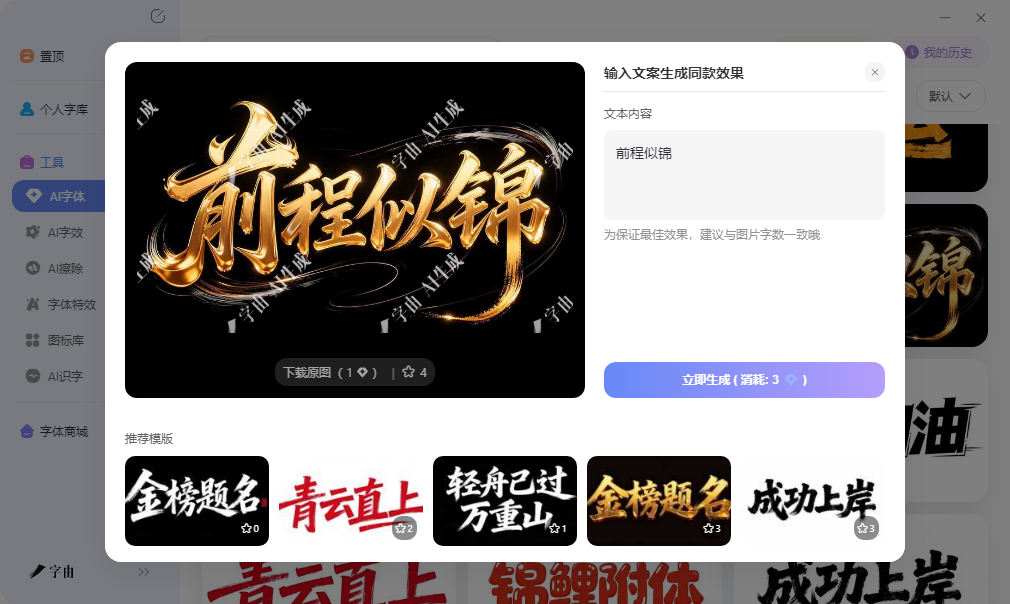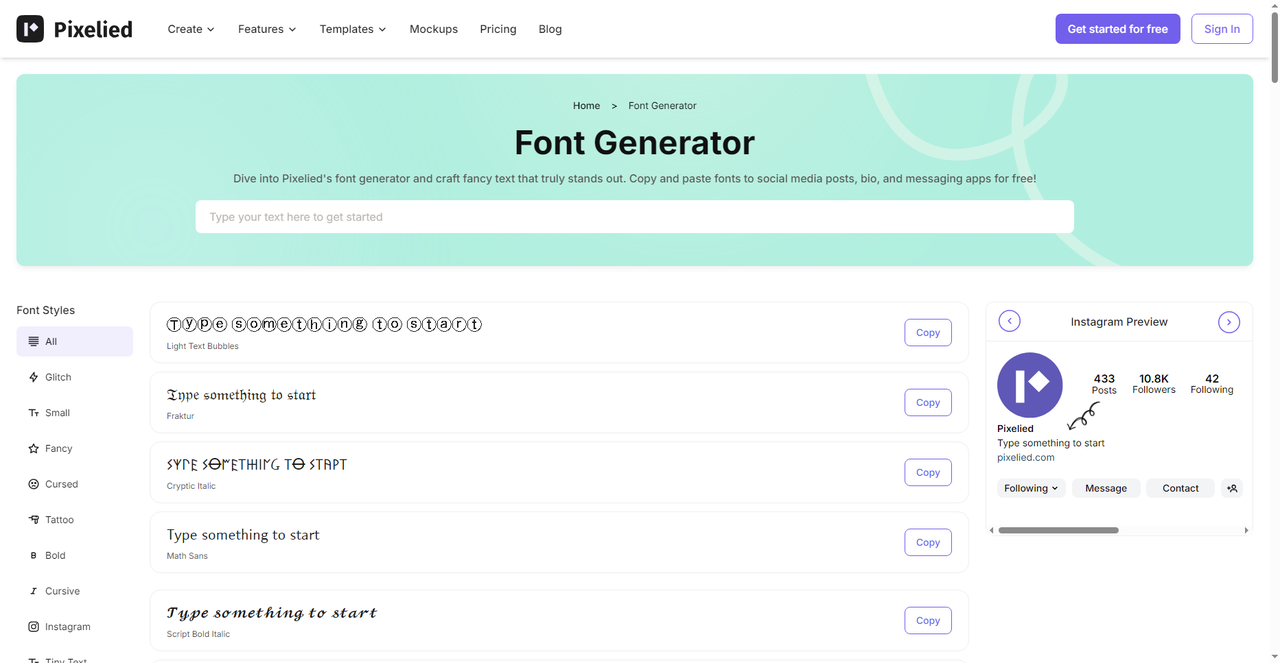
社交媒体上那些带特殊效果的文字,看起来像是用了什么高级设计软件,其实有不少在线工具可以直接生成。输入文字、选一个风格、复制粘贴就能用,不需要安装任何软件。这篇文章整理了五个艺术字体在线生成器免费平台,从中文AI艺术字到英文装饰字体都有,适合做海报标题、社交账号简介、游戏昵称等场景。
字由的AI字体功能和其他几个平台不太一样。其他工具生成的是基于Unicode字符的变体文字,适合用在社交平台的文字输入框里;字由生成的是图片,视觉层次更丰富,也更适合设计项目。
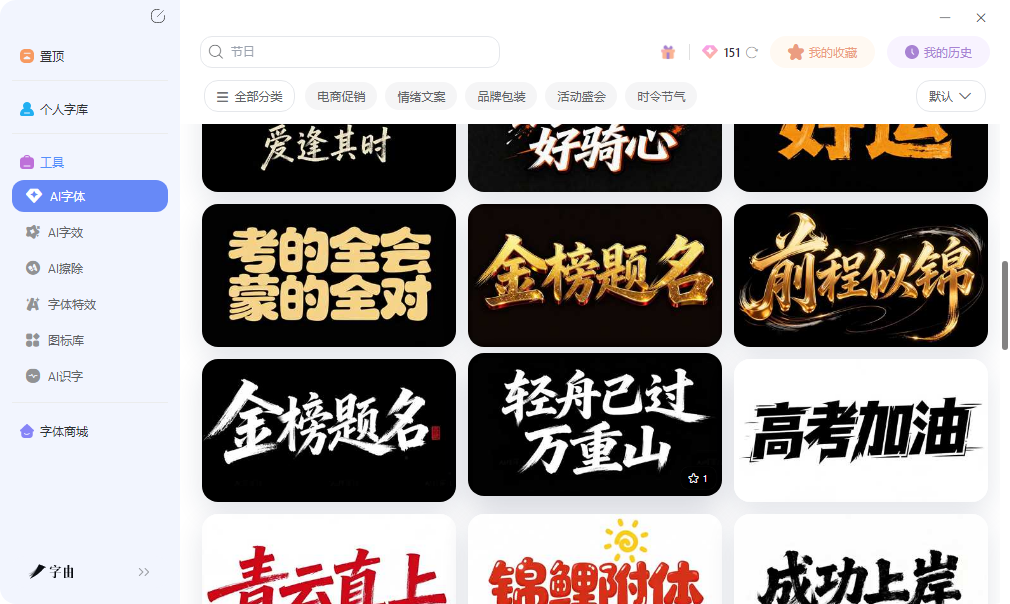
操作上,进入AI字体界面后,从模板库选一个风格方向,覆盖国潮、书法、科技、霓虹、节日主题等多个方向。输入文案,点击生成,大约25秒左右拿到成品。导出格式是PNG,默认透明背景,可以直接放进PS、Canva、剪映等软件里叠加使用。每次生成消耗3个算力点,每天登录送6个点,相当于每日免费生成2张,做几张社交配图或者活动标题完全够用。
AI字效是另一个相关工具,偏向给已有文字加特效。选中一款已激活的字体,再选特效模板,可以给文字叠加发光、投影、渐变等效果。基础面板调字号粗细,进阶面板调配色和效果强度,个性化空间比较足。这个字效功能也有网页版,打开浏览器就能操作,不需要下载客户端。
需要注意的是,AI字体和AI字效生成的是图片,不是可安装的字体文件。如果后续要修改文字内容,需要重新生成。但对于海报标题、Banner文字、封面图这类不需要频繁改字的场景,这个限制影响不大。
Pixelied的Font Generator界面比较直观,顶部输入框里打字,下方实时生成多种风格的变体文字。左侧是风格分类导航,目前能看到的有Light Text Bubbles、Glitch、Small、Fancy、Cursed、Tattoo、Bold、Cursive、Instagram等类型,点击即可切换不同风格系列。
每个生成的文字样式旁边都有一个Copy按钮,点击后复制到剪贴板,直接粘贴到Instagram、Twitter、TikTok的简介或者帖子标题里就能用。右侧还有一个Instagram Preview窗口,可以实时预览文字在社交平台上的显示效果,这个设计挺实用的——有些特殊字符在Instagram上显示正常,换到别的平台可能就变形了,提前预览能避免这个问题。
Pixelied本身是一个综合设计工具,除了字体生成器外还有图片编辑、模板设计等功能。如果只是需要艺术字体在线生成器免费工具来美化社交账号文字,Font Generator这个子功能已经足够,不需要注册就能用。
Fontfy的定位很直接:一个免费的字体生成器,提供80多种独特字体风格。页面顶部的输入框支持最多100个字符,输入完点Generate Fonts按钮,下方就会列出所有可用的文字变体。
生成的结果按分类做了标签过滤,包括IG Fonts、Cool、Fancy、Birthday、Symbolic、Wedding、Valentine等场景化分类。比如要做Instagram账号简介就选IG Fonts标签,做生日祝福文案就点Birthday标签,做情人节相关内容就筛Valentine分类。这种场景化的组织方式比纯按字体名称排列更直观,不需要逐个试就能快速找到合适的风格。
每个生成的文字旁边也有复制按钮,一键粘贴到目标位置。Fontfy的界面比较简洁,功能集中在文字生成和分类浏览上,没有多余干扰。对于只需要一个艺术字体在线生成器免费工具、不想被其他功能分散注意力的用户来说,这种专注度反而是一种优势。
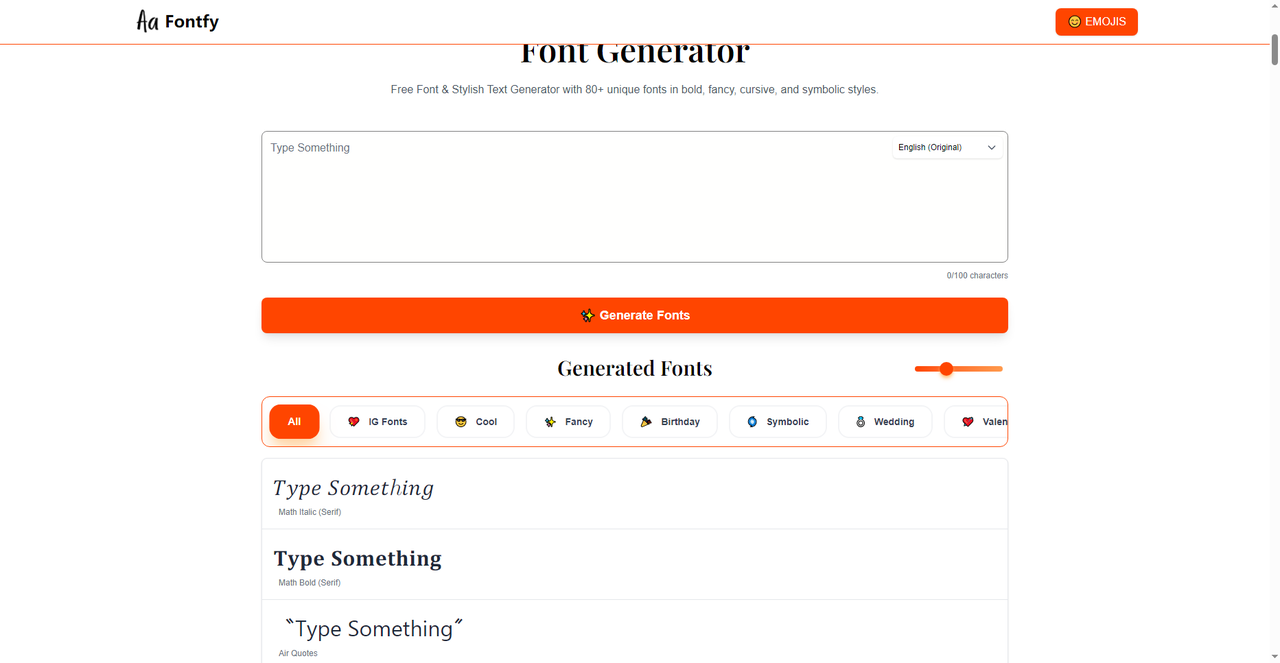
这个Font Generator的界面更简单,顶部输入框打字,下面直接列出Fancy Fonts分类下的各种文字变体。没有复杂的导航和分类,就是输入、生成、复制三步。
页面提供了Lines和Size两个滑块调节选项。Lines控制生成的行数,Size调整显示大小。这种极简的交互适合不需要太多分类筛选、想要快速拿到结果的场景。生成的每个文字样式右侧都有一个复制图标,点击即可复制到剪贴板。
从展示的效果来看,Fancy Fonts分类覆盖了哥特体、草书体、装饰体、手写体等多种风格,变体的数量比较多。作为一个艺术字体在线生成器免费工具,它的优势在于速度——打开网页、输入文字、拿到结果,整个过程不需要任何学习成本。
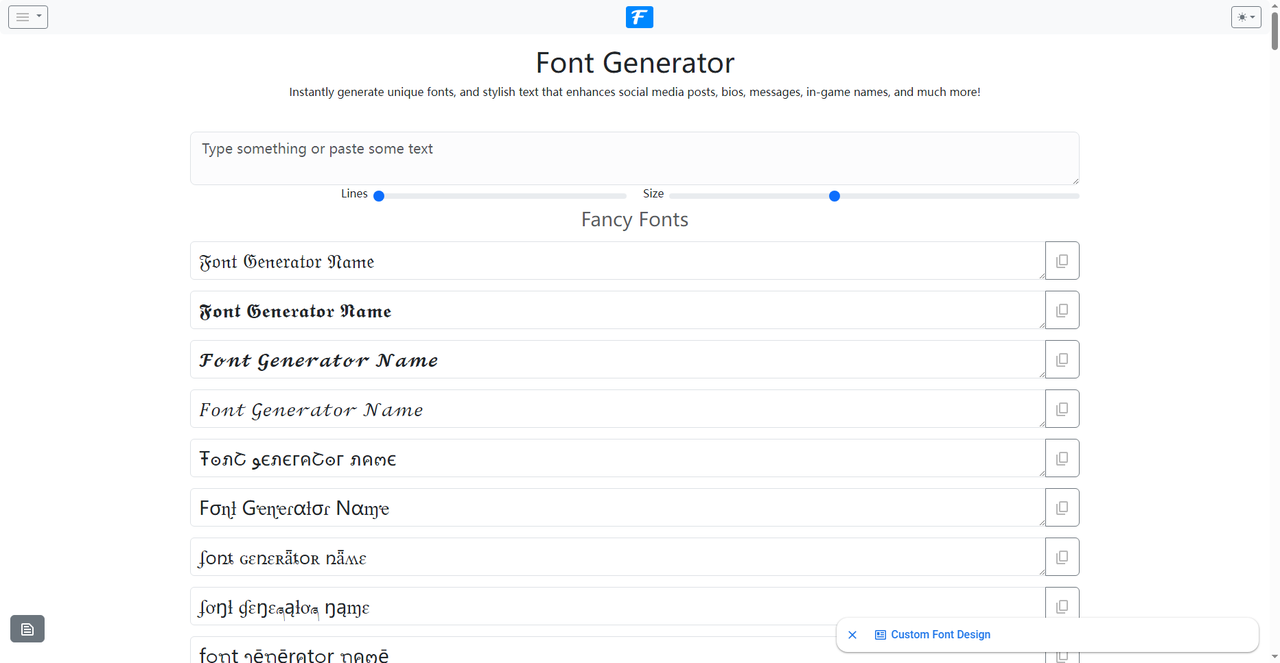
这个Font Generator支持的风格数量比较多,目前展示了184种可用风格,页面还提到总数超过150种。顶部输入框支持多行文字,下面有搜索框可以按风格名称查找,比如输入"Cursive""Bubble""Gothic"等关键词就能快速定位到对应分类。
结果按风格大类做了分组,比如Mathematical & Scientific分类下有Mathematical Bold、Mathematical Italic等变体。每个结果旁边都有Copy按钮。页面还会显示当前输入的字符数,帮助你控制长度,避免超出社交平台的文字限制。
150多种风格在同类工具中算是数量比较多的,覆盖的装饰方向也更广。对于需要大量风格选择、喜欢在众多选项里慢慢挑的用户来说,这个艺术字体在线生成器免费平台的资源丰富度比较有吸引力。
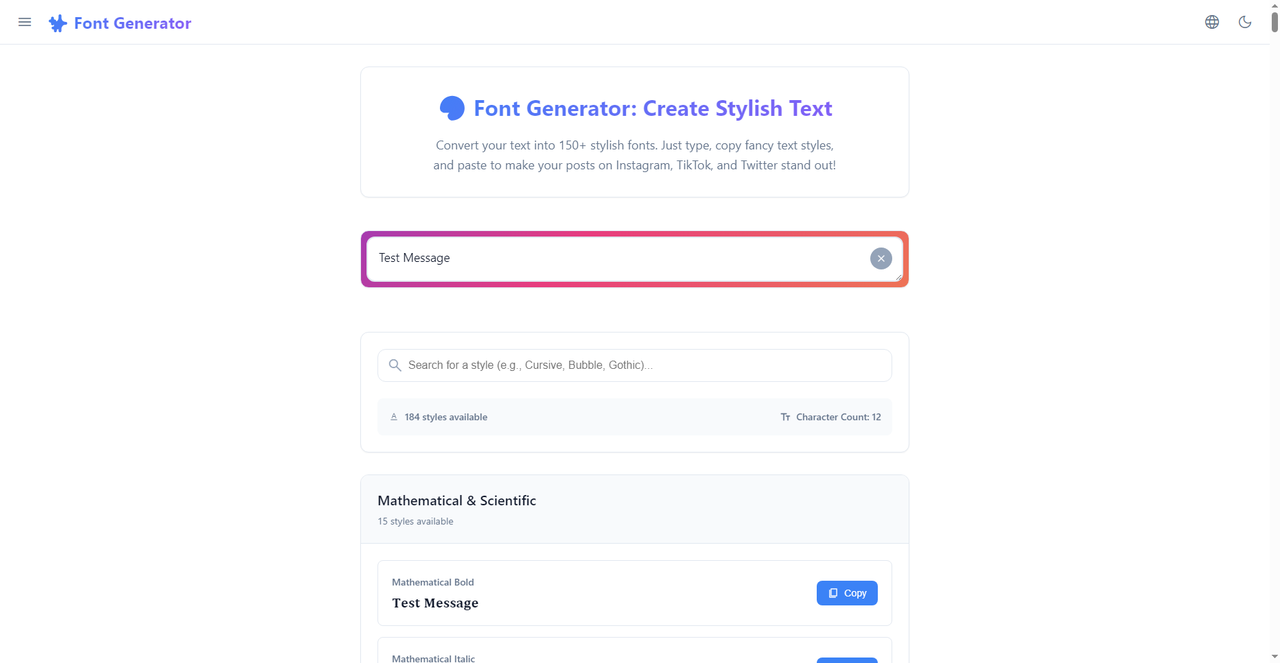
如果只是需要一段带特殊效果的文字发到社交平台,Pixelied的Instagram预览功能比较贴心,Fontfy的场景化分类找起来很快,Font Generator的极简界面适合快速出结果,150+风格的Font Generator选择最多。但如果要做中文海报标题、Banner设计这类需要图片素材的项目,字由的AI字体和AI字效生成的PNG图片视觉层次更强,透明背景直接拖进设计稿,配合每日免费算力,作为艺术字体在线生成器免费方案更贴合设计工作流。